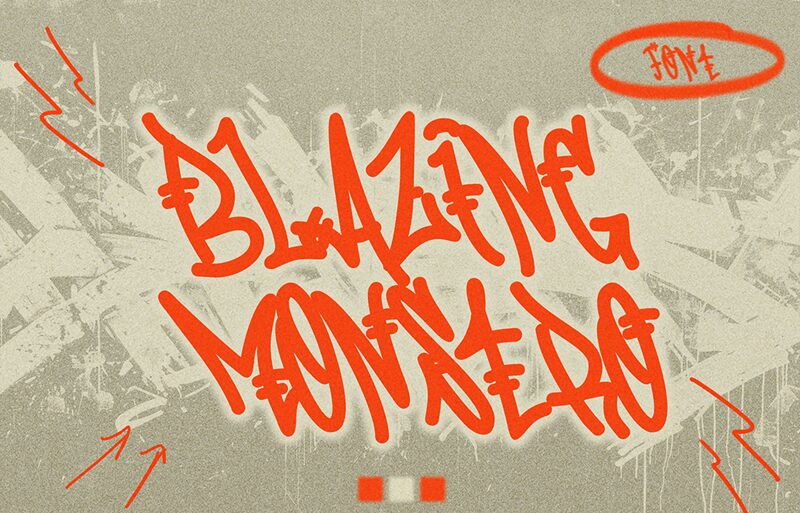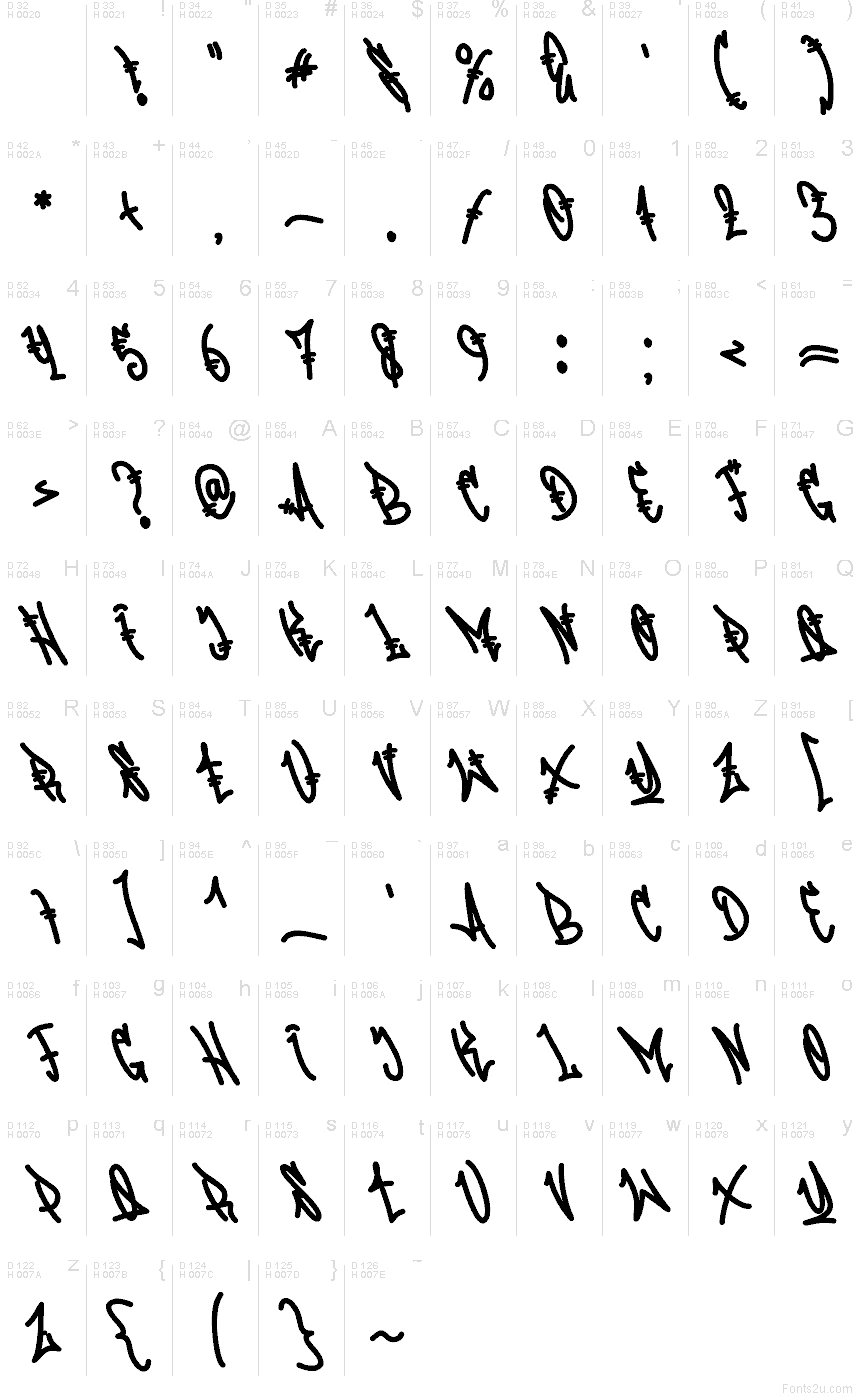
Blazing Monstro di Muhammad Panji Ramdhani di Figuree Studio è un font graffiti gratuito dal ritmo selvaggio, caratterizzato da tratti affilati come artigli. Le lettere sembrano dipinte a spray in tutta fretta - appuntite, leggermente caotiche e ben compresse - così le tue parole colpiranno come un tag su cemento fresco. È d'impatto senza bisogno di effetti aggiuntivi.
Usa Blazing Monstro su loghi streetwear, poster da skate, copertine musicali, miniature YouTube, overlay per il gaming, set di adesivi e volantini per eventi underground per mantenere un'energia cruda e carica di inchiostro. Impostalo in grande con un tracking generoso per far respirare le punte e abbina questo font gratuito a un sans serif pulito per i dettagli più piccoli.